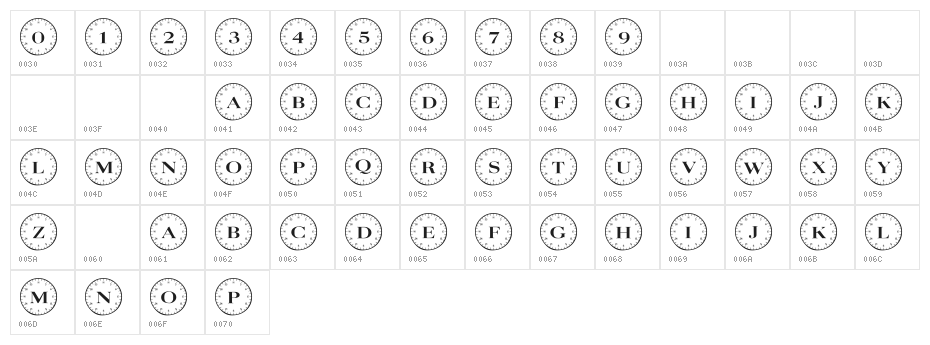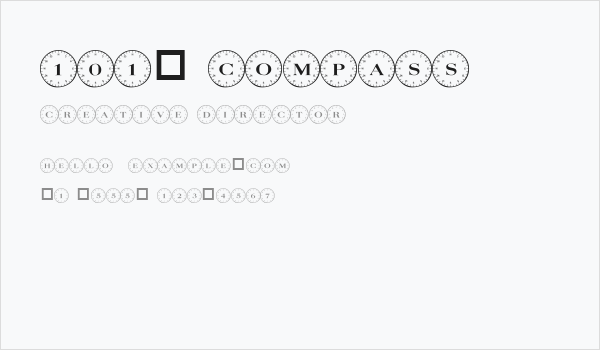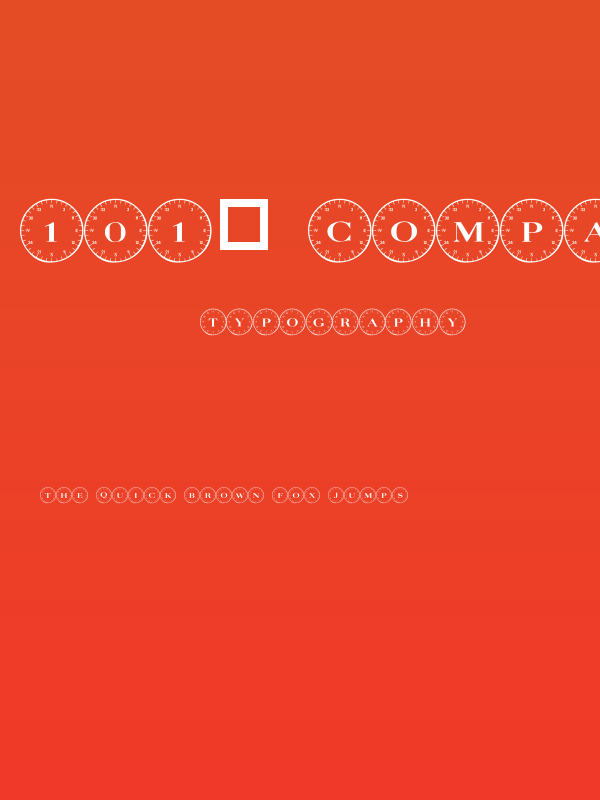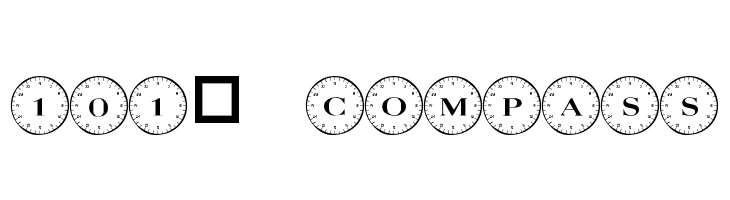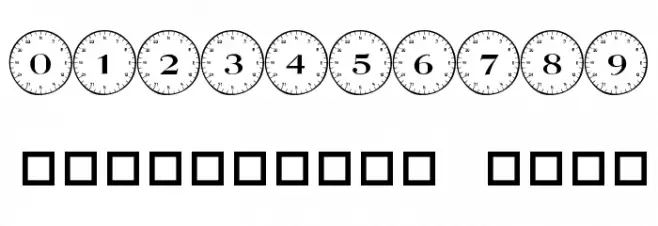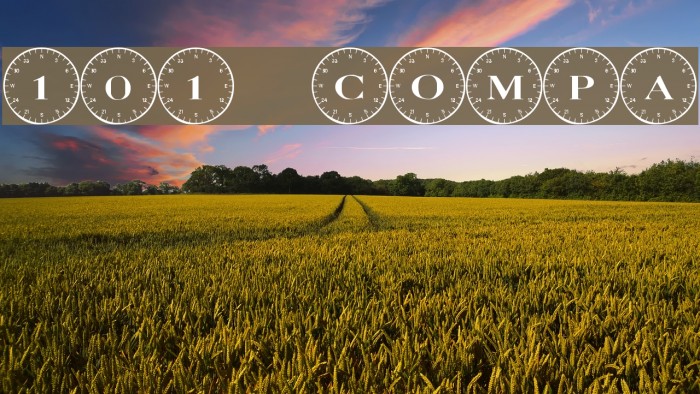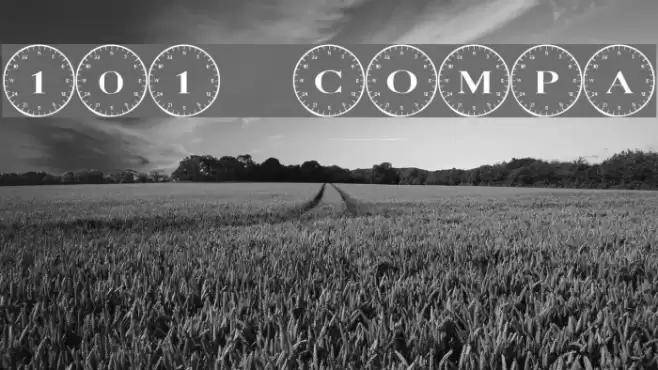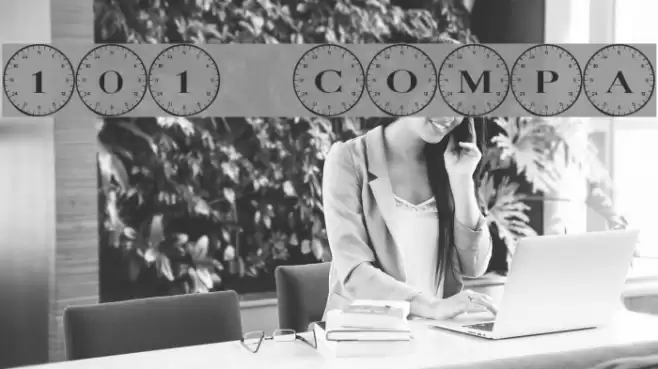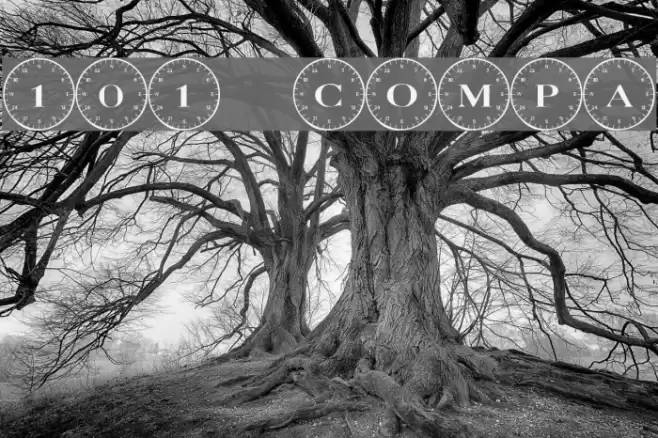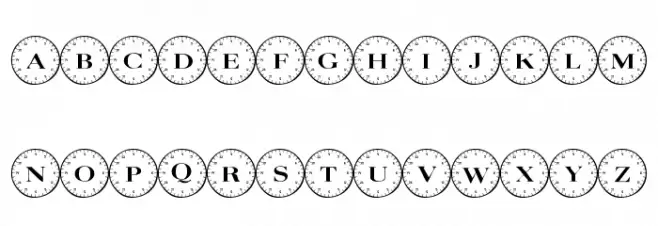
101! Compass Font
| Anwendungsfall | Logos, Headlines, Posters |
| Vorgeschlagene Projekte | Ideal for themed events, adventure-themed branding, educational materials, or decorative posters. |